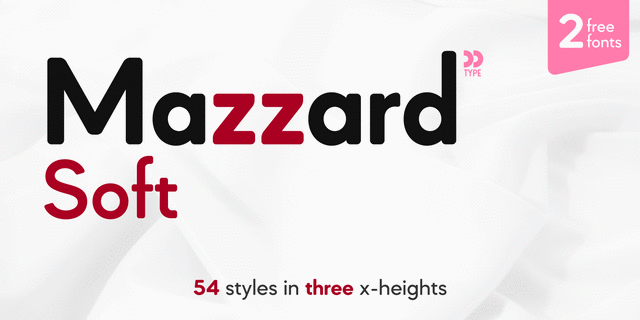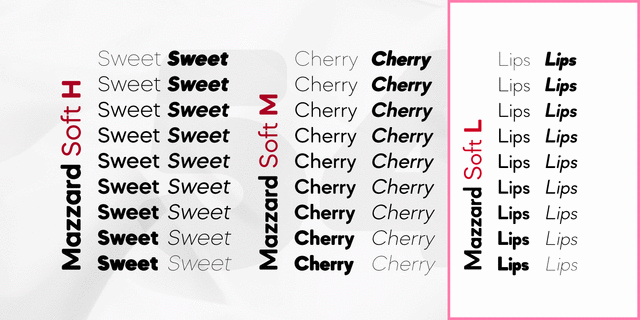
Mazzard Soft L – это часть шрифтового семейства Mazzard Soft, которое в свою очередь является версией с закруглёнными углами суперсемейства Mazzard. В этой версии есть ещё два геометрических гротеска, который отличаются высотой строчных знаков (H и M).
Mazzard Soft L имеет широкий спектр языковой поддержки, включая кириллицу, и предлагает большой выбор альтернативных глифов.
Шрифт разработал Олег Лищук в 2019 году.